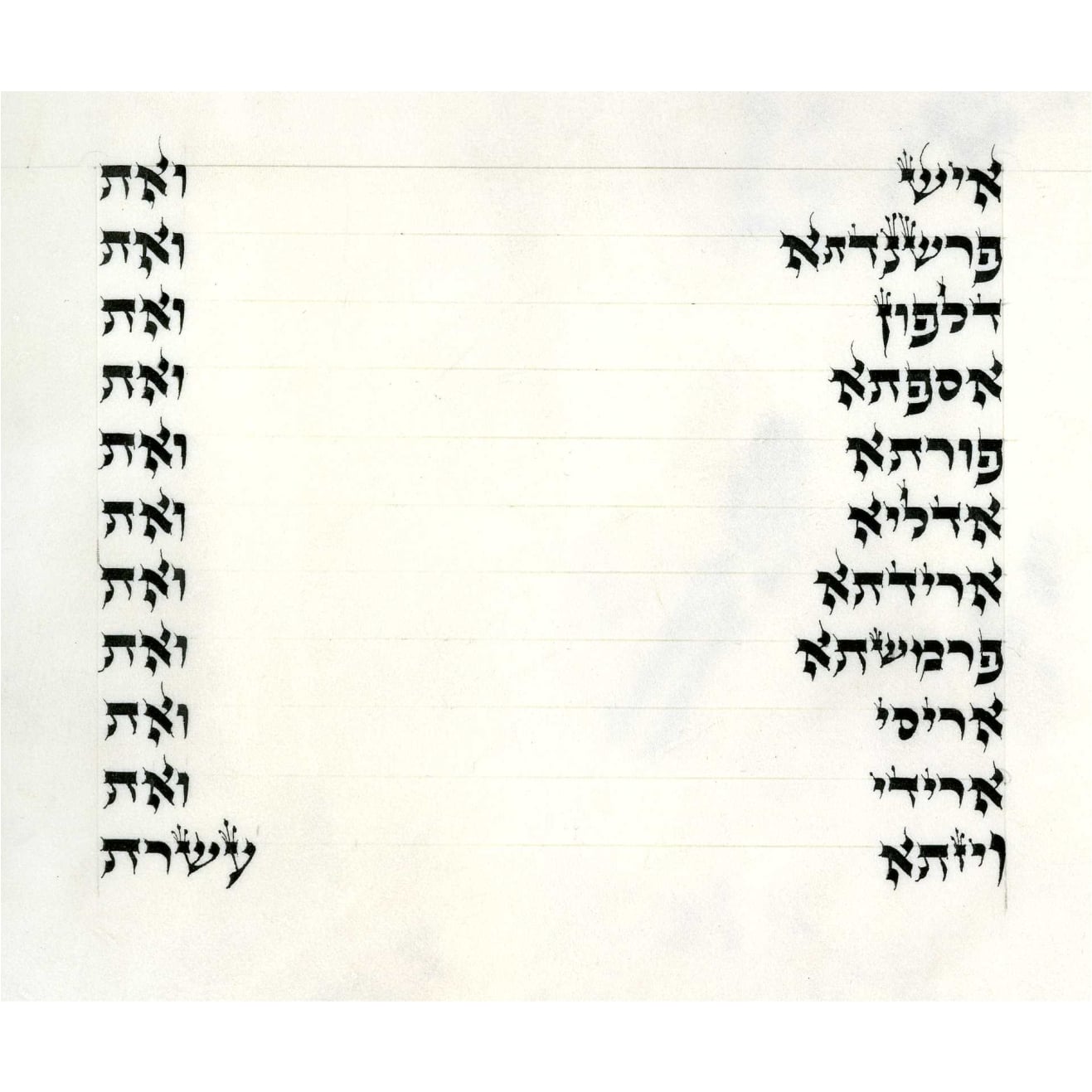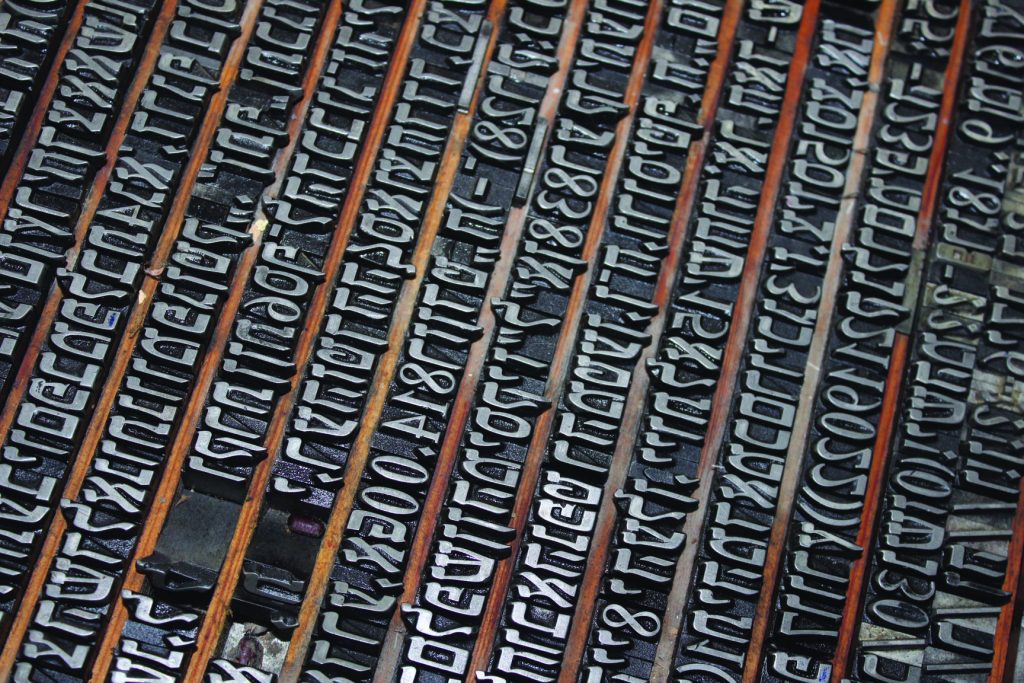
הסיפור המרתק של טיפוגרפיה בעברית, מעיצובים ראשוניים על לוחות חרס ועד לעידן הדיגיטלי של היום, מספר את סיפורה של שפה עתיקה שהתחדשה לאורך
דורות. כבר בימי הביניים, התפתחו פונטים בעברית שהבליטו את האופי והעושר התרבותי של הכתב העברי, במיוחד בכתבי יד וספרים קדושים. עם הגעת הדפוס, השתנה המשחק: היכולת להדפיס טקסטים בקנה מידה גדול הובילה לשינויים עמוקים בגישה לקריאה וללימוד.
במאה ה-20, עם קפיצת המדרגה הטכנולוגית והעברת הכתב למדיום הדיגיטלי, נוצרו פונטים עבריים חדשים שתרמו להמשך ההתפתחות האסתטית והתפקודית של הכתב. כיום, בעידן האינטרנט, טיפוגרפיה בעברית לא רק ששומרת על מסורת אלא גם מחדשת אותה, כאשר מעצבים עושים שימוש בכלים דיגיטליים ליצירת פונטים שמדברים בשפה ויזואלית עכשווית וחדשנית.
הסיפור המרתק של טיפוגרפיה בעברית, מעיצובים ראשוניים על לוחות אבן וחרס ועד לעידן הדיגיטלי של היום, נתחיל עם הופעת הכתב העברי המקראי. עולמם של הכותבים בתקופה זו היה מוגבל לחומרים הזמינים, הם השתמשו בכלים פרימיטיביים לחקיקת אותיות על גבי משטחים קשים ולא נוחים. האותיות היו פשוטות ותכליתיות, מותאמות לתנאים אלו ומשקפות את הצורך להעביר מסרים בצורה ברורה ויעילה.
כתב עברי קדום חצוב על כותל נקבת השילוח (ויקיפדיה)
בימי הביניים, כשעם ישראל התפזר ברחבי אירופה והמזרח התיכון, כל קהילה יהודית התחילה לפתח ניב טיפוגרפי משלה. השפעות הסביבה והאינטראקציה עם תרבויות אחרות הביאו ליצירת כתבי יד מפוארים ומעוצבים בסגנונות מזרחי, ספרדי ואשכנזי. אלו לא רק שימשו לתפילה או לימוד אלא גם הדגישו את הזהות התרבותית והדתית של הקהילות.
כתיבת סת״ם בסגנון אשכנזי (מאת איזי פלודבינסקי)
סגנון כתיבה ספרדי מרובע פורמלי מימי הביניים. (דוד גולדשטיין)
בתקופת הרנסאנס ועם המצאת הדפוס על ידי יוהאן גוטנברג, נעשה קפיצת מדרגה משמעותית בהנגשת הטקסטים העבריים. היכולת להדפיס ספרים בכמויות גדולות פתחה את הדלת להפצה רחבה של ידע ומידע. דמויות כמו שונצינו באיטליה הובילו את תהליך הדפסת ספרים עם פונטים בעברית, ובכך הפכו את הפונט האשכנזי הגותי לנפוץ בקרב הקהילות היהודיות באירופה.
אותיות עופרת של גופן פרנק-ריהל צר הסדריה, מוזאון היסטוריית הדפוס, כפר קיש (מגזין סגולה)
עם קום מדינת ישראל וההתחדשות הלאומית, נוצרים פונטים עבריים אייקוניים כמו "נרקיס" ו"מרים", שתוכננו לשקף את הזהות החדשה של המדינה. פונטים אלה תרמו לבניית זיהוי חזותי ייחודי ששילב בין המסורת לבין החדשנות של החברה הישראלית המתפתחת וקידמו רבות את הטיפוגרפיה העברית המודרנית.
פונט מרים מתוך קטלוג בצלאל
בעידן הדיגיטלי, פונטים בעברית ממשיכים להתפתח ולהשפיע, כאשר טכנולוגיות חדשות מאפשרות יצירת פונטים דיגיטליים מתקדמים. יכולת השליטה במאפיינים כמו משקל, רוחב וגוון מאפשרת גמישות עיצובית רחבה, מה שמתרגם לעיצובים אישיים וייחודיים שמתאימים לצורכים שונים ותומכים במגוון שפות ופלטפורמות.
פונט דינמי בפעולה
טיפוגרפיה אינה רק עניין של עיצוב – היא משקפת את ההיסטוריה העשירה והמתפתחת של שפה עתיקה שחודשה לחיים חדשים במדינה עצמאית. כל פונט מספר סיפור של תקופה, של קהילה, של תרבות.
כשאתם קוראים טקסט עם פונטים בעברית, כל אות מקבלת משמעות עמוקה יותר ממה שהעין רואה. האותיות מגלמות את המסע שעברה השפה העברית, מהשתקפות התקופות השונות בהיסטוריה ועד להתבטאות בטקסטים חדשניים ומודרניים.
אז בפעם הבאה שאתם מתבוננים בכותרת בעיתון או קוראים ספר בעברית, זכרו שאתם נוגעים בחלקיק של היסטוריה ותרבות. הפונטים שלנו אינם רק כלי לקריאה, אלא גם להבנת המקום ממנו באנו ולאן אנחנו פונים.
בעידן הדיגיטלי שלנו, שבו הכול נראה ממוחשב ואוטומטי, עדיין קיים מקום מיוחד לסוגי פונטים בעברית כתב יד בעולם הטיפוגרפיה. מעצבים ואמנים רבים מוצאים דרכים חדשניות לשלב את הכתב היד המסורתי בעיצובים מודרניים ויוצרים פונטים שמדמים כתב יד אנושי. השימוש בפונטים אלו מאפשר להעביר תחושה של אותנטיות וחמימות שלא תמיד ניתן להשיג באמצעות פונטים דיגיטליים רגילים. הערך של כתב יד בעידן הדיגיטלי מוכיח שאף על פי הטכנולוגיה המתקדמת, ישנה חשיבות רבה לאלמנט האנושי והמסורתי בעיצוב הוויזואלי.
כל שינוי בעיצוב הטיפוגרפיה בעברית משקף תהליך תרבותי והיסטורי. מהעת הקדומה ועד לימינו, השינויים בפונטים לקחו את האסתטיקה, הטכנולוגיה והצורכים של התקופה בחשבון. דרך הפונטים ניתן ללמוד על התפתחות השפה, על הזהות הלאומית ועל ההשפעות החיצוניות שהשפיעו על החברה היהודית והישראלית.
בחירת פונטים בעברית עם ניקוד בפרויקטים גרפיים יכולה לשפר משמעותית את הקריאות והבהירות של הטקסט, במיוחד בקרב קהלים שעשויים להיות פחות מקצועיים בשפה העברית או כאשר הטקסט כולל מילים עם משמעויות שונות שהניקוד יכול להבהיר. הניקוד מוסיף עומק לטקסט ומסייע להעברת המסר בצורה מדויקת וברורה יותר. בנוסף, השימוש בניקוד יכול להוסיף ערך אסתטי לעיצוב ולהפוך אותו לייחודי ומושך יותר, מה שמחזק את המותג ואת הזיהוי החזותי של הפרויקט.
בעידן הדיגיטלי, טכנולוגיות כמו פונטים דינמיים ופונטים בעלי מאפיינים משתנים הובילו ליכולת שליטה מדויקת יותר בעיצוב הפונט. הדבר מאפשר למעצבים להתאים את הפונט לצרכים ספציפיים, לשפות רבות ולפלטפורמות שונות, מה שתורם לעיצוב מרהיב וגמיש יותר.